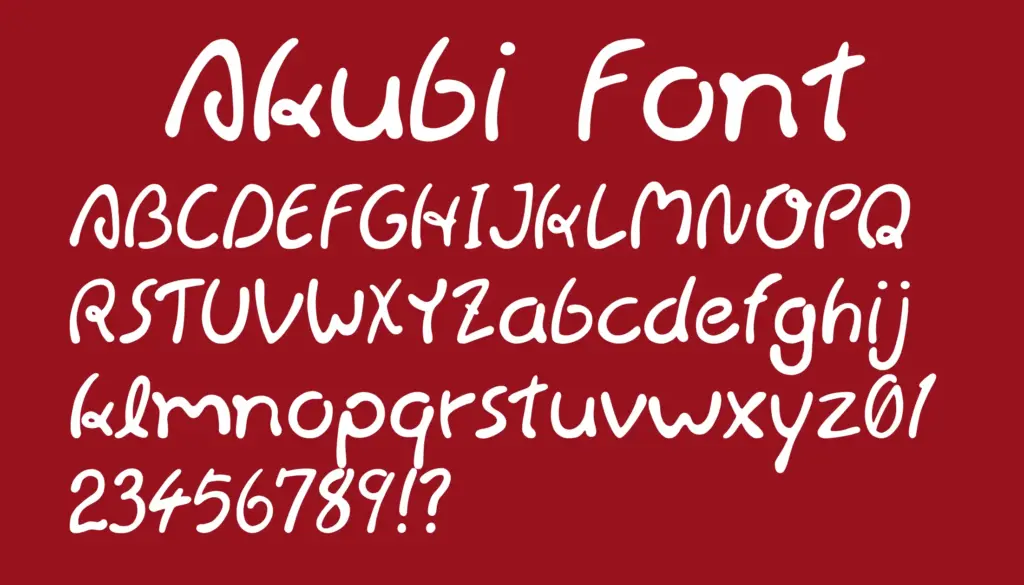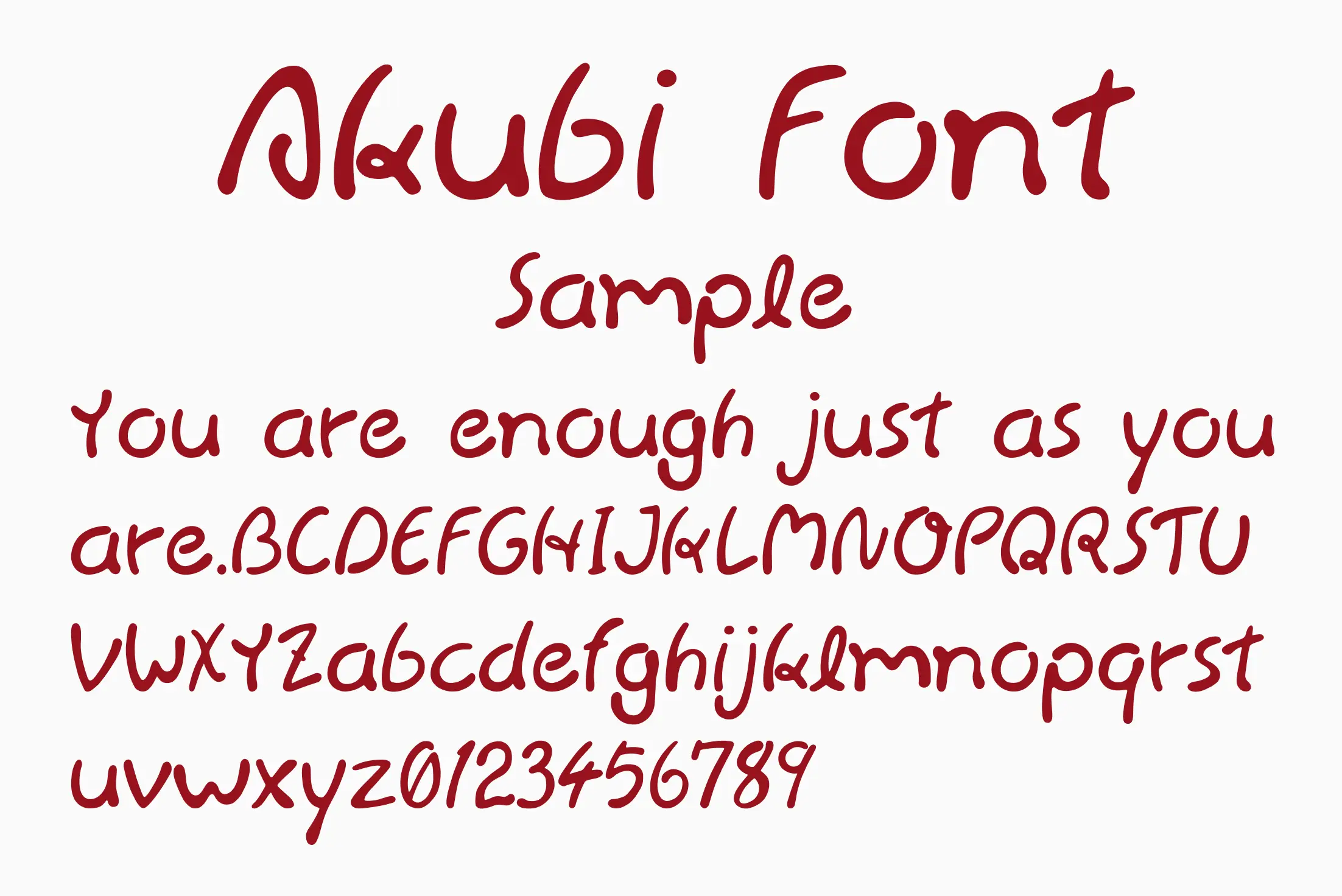
「のんびりとした空気感」をまとった英字手書き風フォントです。ラフなインクの滲みを思わせる筆跡が特徴で、柔らかく丸みのある文字が親しみやすく、やさしい印象を与えます。カフェのロゴ、英語タイトル、ZINEの装飾、SNS画像などにおすすめ。個人利用を中心に、雰囲気づくりに役立つあたたかみのある欧文フォントです。
Akubi Font